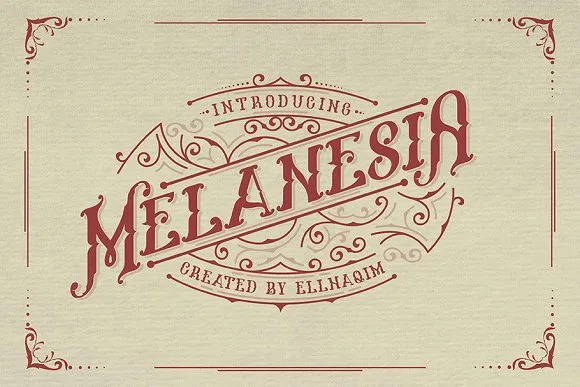
A Melanesia Typeface é uma família vintage de fontes lançada por ellhaqim, perfeitamente projetada para variados propósitos de design e arte. Suas linhas elegantes e sua simpatia antiga tornam-a ideal para um amplo range de aplicativos, como rótulos de bebidas, selos de café, logotipos, cartões de cumprimento ou embalagens, até mesmo identidades empresariais, designs artesanais ou qualquer projeto DIY. Além disso, é perfeita para capas de livros, fontes para casamentos vintage, criações retro e para qualquer outra aplicação que deseje dar um toque moderno e atraente ao seu trabalho de design ou arte.